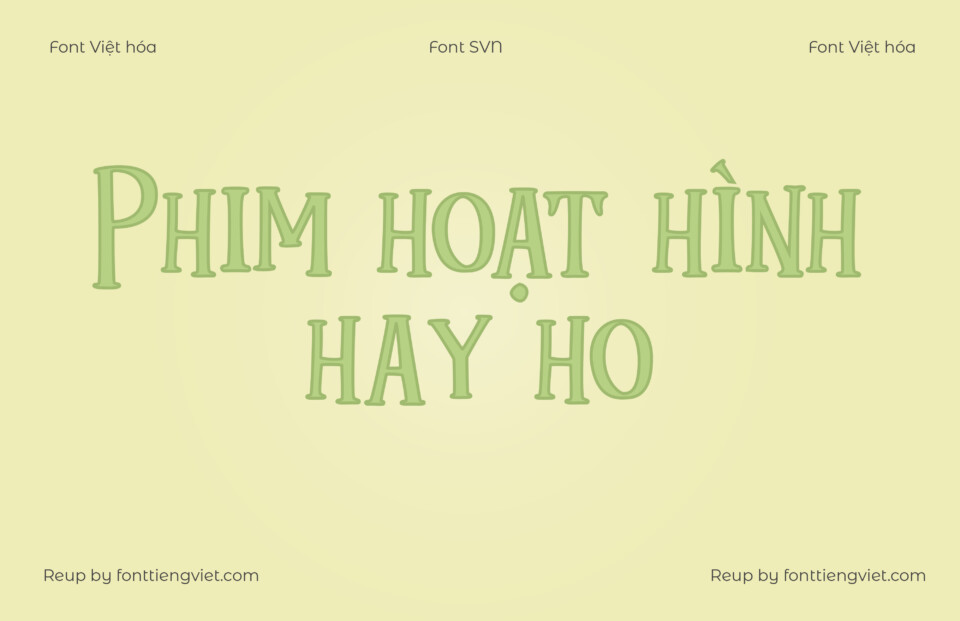
Font Việt hóa SVN Mukadua
Trong thế giới thiết kế đồ họa, việc tìm kiếm một bộ Font Việt hóa SVN Mukadua chất lượng là điều vô cùng quan trọng để tạo nên những sản phẩm ấn tượng. Đây là một bộ Font Miễn Phí mang phong cách Serif hiện đại, kết hợp hài hòa giữa nét cổ điển và sự tinh tế. Với đường nét thanh mảnh nhưng chắc chắn, Mukadua cực kỳ phù hợp cho các dự án đòi hỏi sự chuyên nghiệp và tính thẩm mỹ cao trong môi trường học đường.
Ưu điểm nổi bật của Font Việt hóa SVN Mukadua
Thiết kế tối ưu và dễ đọc
Bộ Font Việt hóa SVN Mukadua được cộng đồng thiết kế đánh giá cao nhờ khả năng hiển thị rõ nét trên cả màn hình kỹ thuật số và ấn phẩm in ấn. Các ký tự được tinh chỉnh kỹ lưỡng, giúp người xem không bị mỏi mắt khi đọc các đoạn văn bản dài. Điều này rất có lợi khi các bạn học sinh, sinh viên sử dụng font để làm slide thuyết trình hoặc báo cáo khoa học.
Hỗ trợ tiếng Việt hoàn chỉnh
Điểm mạnh nhất của phiên bản này chính là việc đã được việt hóa chỉn chu. Toàn bộ các dấu câu và ký tự đặc biệt trong tiếng Việt đều được xử lý chuẩn xác, không xảy ra hiện tượng lỗi font hay nhảy chữ. Bạn có thể tự tin sáng tạo các tiêu đề sách, bìa tiểu luận hay các banner sự kiện nhà trường một cách nhanh chóng và hiệu quả nhất.
Ứng dụng Font Việt hóa SVN Mukadua trong thực tế